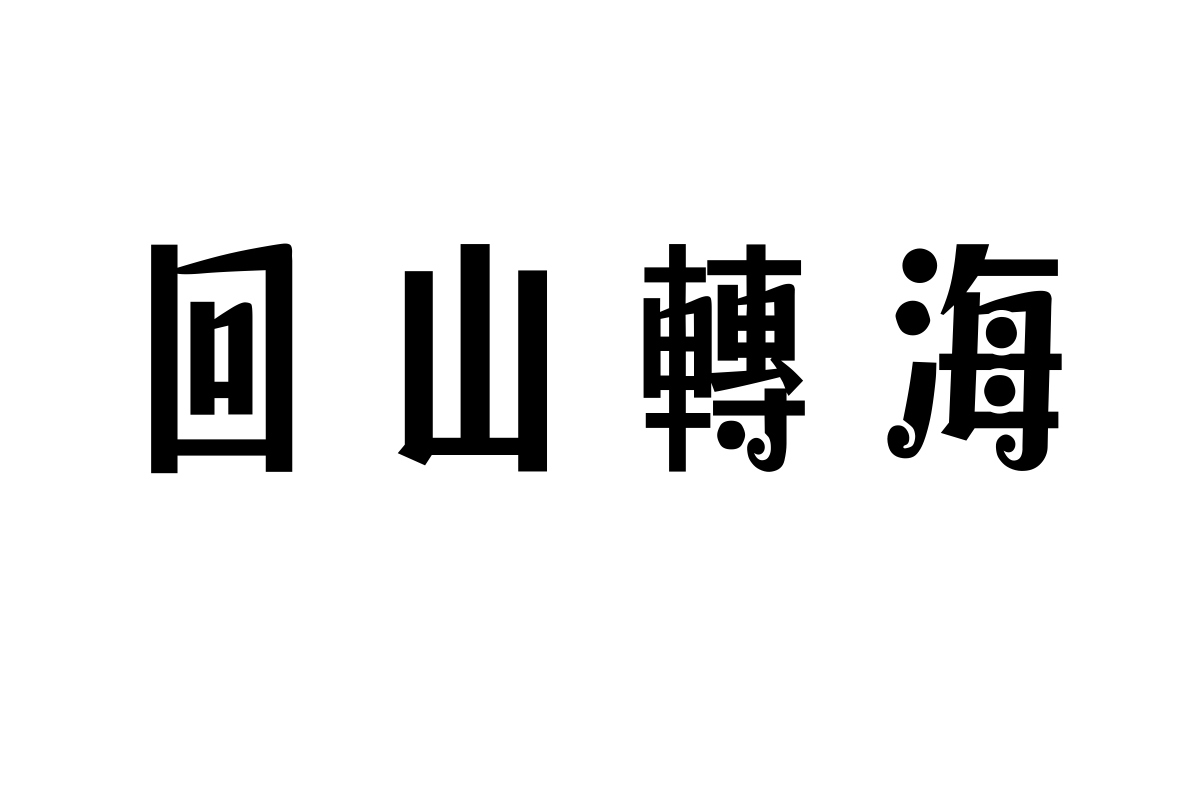
汉仪长艺体是汉仪公司推出的一款艺术字体,具有独特的风格和韵味。这款字体采用现代设计手法,结合传统书法元素,呈现出一种简约而不失个性的视觉效果。
汉仪长艺体的特点如下:
1. 字形优美:汉仪长艺体的字形线条流畅,结构紧凑,给人一种优雅、精致的感觉。同时,字体的大小、粗细、间距等都可以自由调整,满足不同场合的需求。
2. 风格独特:汉仪长艺体融合了现代设计元素,如简洁的线条、圆润的轮廓等,使得字体更具现代感。同时,字体中还融入了一些传统书法的元素,如撇、捺、点等,使得字体既有现代感,又不失传统文化的韵味。
3. 适用范围广泛:汉仪长艺体适用于各种印刷品、广告、包装、网站等多种应用场景。无论是企业宣传、产品介绍还是个人作品,都可以轻松应用这款字体,展现独特的艺术魅力。
总之,汉仪长艺体是一款集美观、实用、易用于一体的艺术字体,适合各类设计师和印刷从业者使用。